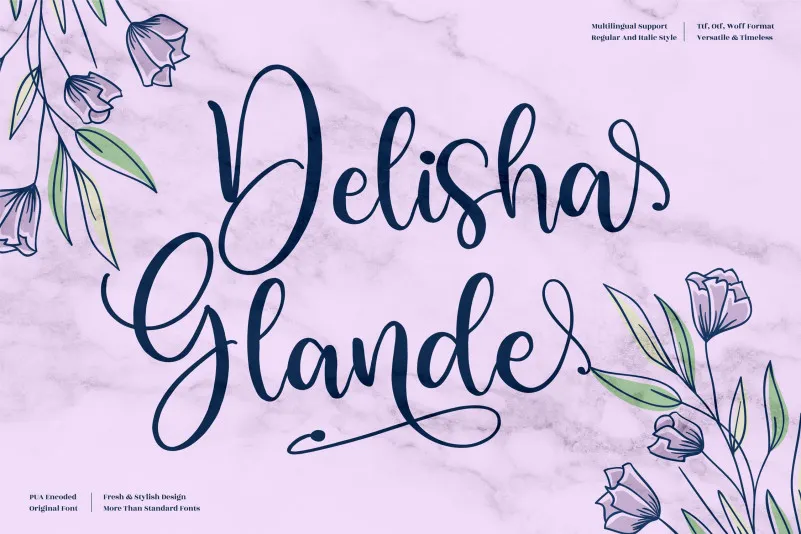
Delisha Glande Font – Fonte Grátis
Delisha Glande Font
A fonte ‘Delisha Glande’ é uma elegante tipografia romântica que se destaca por sua delicadeza e graça, perfeita para qualquer projeto onde um toque de sofisticação seja necessário. Ideal tanto para logomarcas quanto para embalagens e papéis de presente, a ‘Delisha Glande’ traz uma atmosfera amigável que enriquece o design. Seja em mugs decorativos ou cartões de visita, esta fonte garante um toque especial e delicado. Compreende-se também sua utilidade para estampas em camisetas e materiais diversos como papel reciclado ou adesivos. ‘Delisha Glande’ é uma escolha ótima para qualquer projeto que procure harmonia, estilo e um toque de romantismo nos seus detalhes. Seja este um novo projeto editorial, a publicidade digital ou até mesmo eventos especiais em sua loja. A ‘Delisha Glande’ é certamente o complemento perfeito para todos os projetos que desejam destacar-se com uma tipografia única e encantadora.